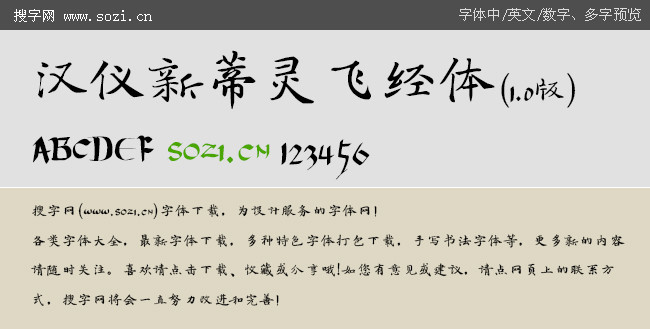
漢儀新蒂靈飛經(jīng)體1.0
搜字網(wǎng)提供一款漢儀新蒂靈飛經(jīng)體1.0字體下載,漢儀新蒂靈飛經(jīng)體是一款漂亮的古風(fēng)手寫字體。由漢儀新蒂工作室出品,漢儀新蒂工作室成立于2016年,由漢儀字庫與新蒂字體聯(lián)合成立,本字體字跡娟秀得體,更顯飄動靈敏之氣,適合應(yīng)用于海報設(shè)計(jì)、書籍設(shè)計(jì)、藝術(shù)設(shè)計(jì)、包裝設(shè)計(jì)等應(yīng)用。(本字體為個人非商用版,如需要商用請聯(lián)系漢儀公司購買版權(quán))